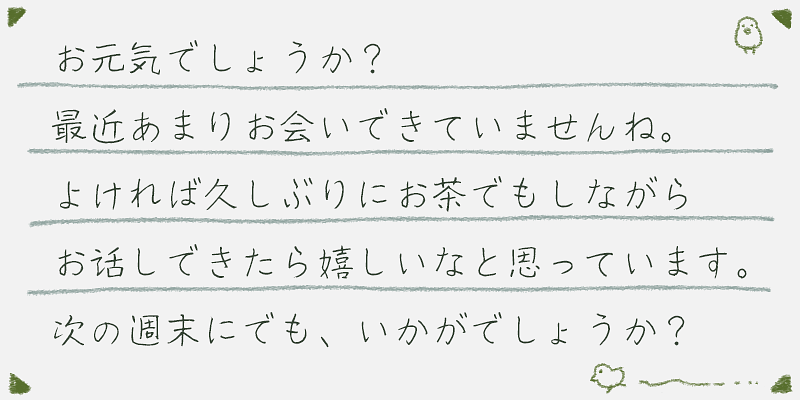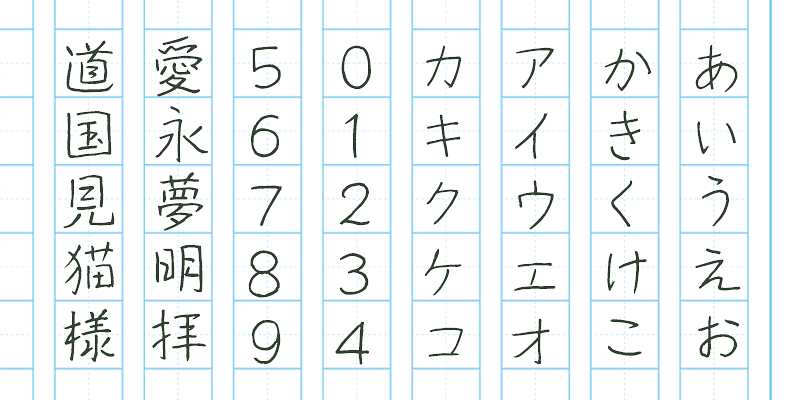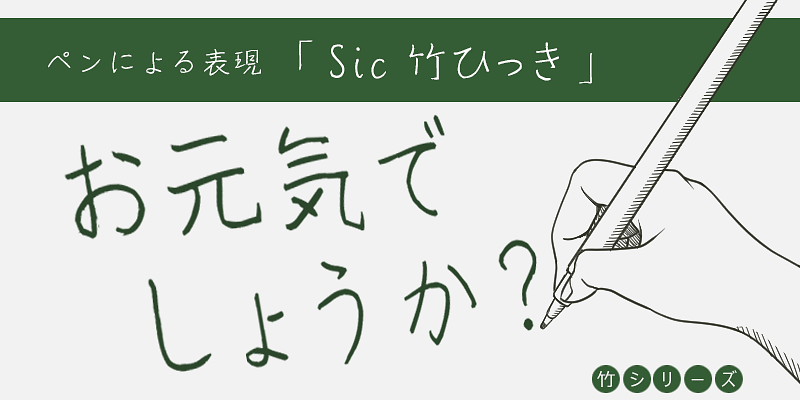
Les polices créées par feu Takeharu Suzuki ont été développées sur la base de sa vaste expérience, allant du lettrage aux polices bitmap, aux polices de traitement de texte et aux polices d’écriture au pinceau. Il a notamment cherché à créer une « police gothique sans stress pour le texte horizontal », ce qui a conduit au développement du design très lisible de la police standard de Windows, Meiryo.
La diversité de ses créations typographiques s’étend non seulement aux polices de style pinceau manuscrites chaleureuses et aux polices de base, mais aussi aux polices gothiques, stylisées et aux polices d’affichage. Ses polices peuvent être utilisées pour un large éventail d’applications, y compris les publicités, les vidéos et les médias numériques. Elles apportent une touche d’originalité et sont très appréciées.